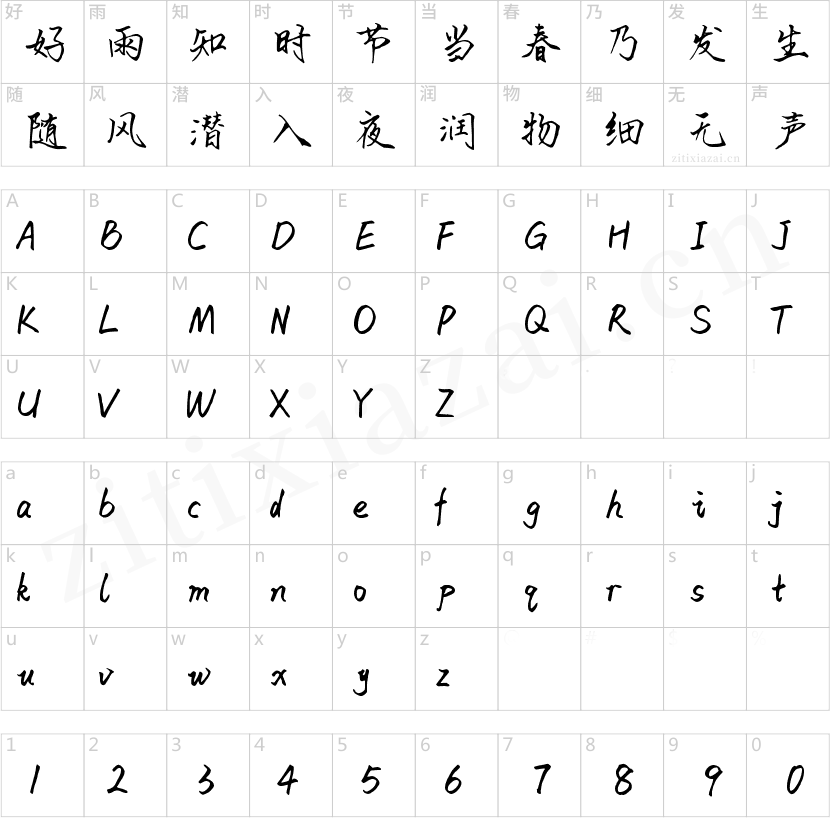
Aa惊鸿难抵梦重重
Aa惊鸿难抵梦重重字体
Aa惊鸿难抵梦重重是一款非常具有艺术性的字体,它的设计灵感来源于对古典艺术的研究,同时又融入了现代字体设计的元素。字形优美,笔画粗细变化自然,给人以大气、典雅的感觉。Aa惊鸿难抵梦重重是一款既传统又现代的字体,它的设计充满艺术感,美观大方,实用性也非常强。无论是对于设计师还是对于普通读者来说,都是一种非常不错的字体选择。Aa惊鸿难抵梦重重适合用于具有艺术感的场合,比如海报、宣传单张、书籍封面等。由于其字形流畅且具有动态感,也适合用于大量的文本排版,如报纸、杂志等。